「周りと差をつけたい人のためのデザインフォント集」の気になる中身をご紹介
圧巻の132書体を収録!MONTREUX GROTESK
132書体・6スタイル・80以上のリガチャ(合字)を収録したサンセリフフォント「MONTREUX GROTESK」。通常価格199ドルのMONTREUX GROTESKがこのバンドルなら3,200円で手に入ります。
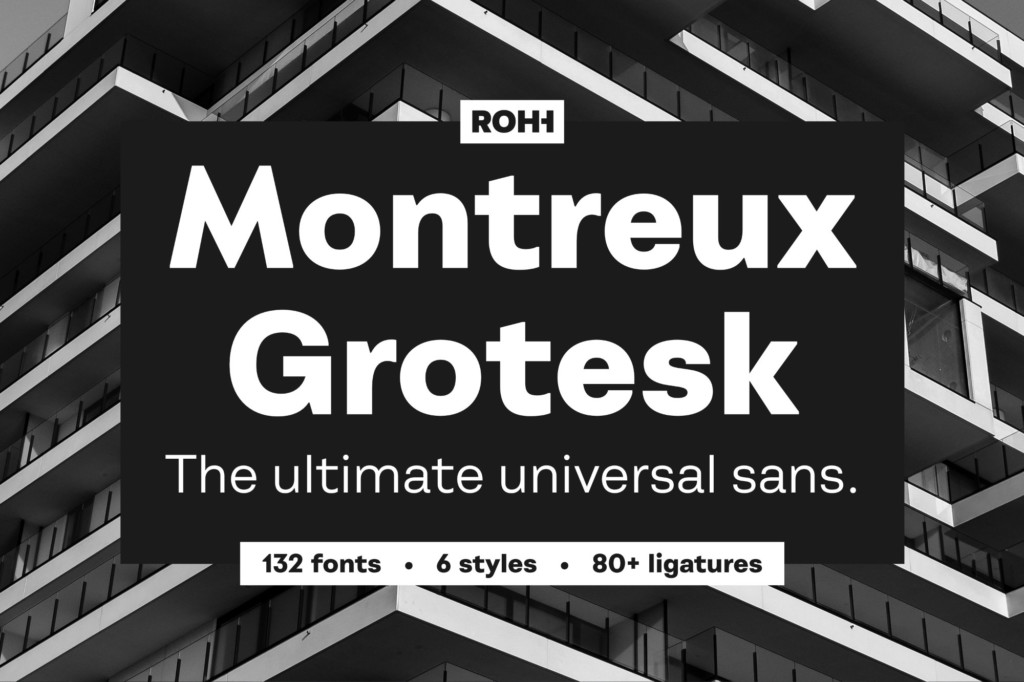
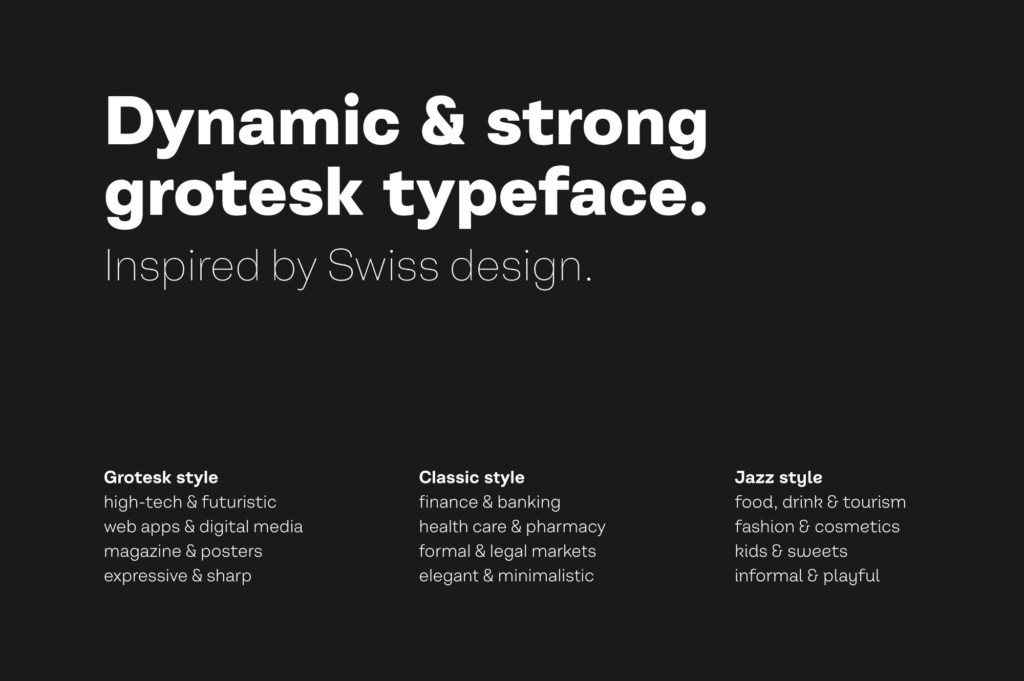
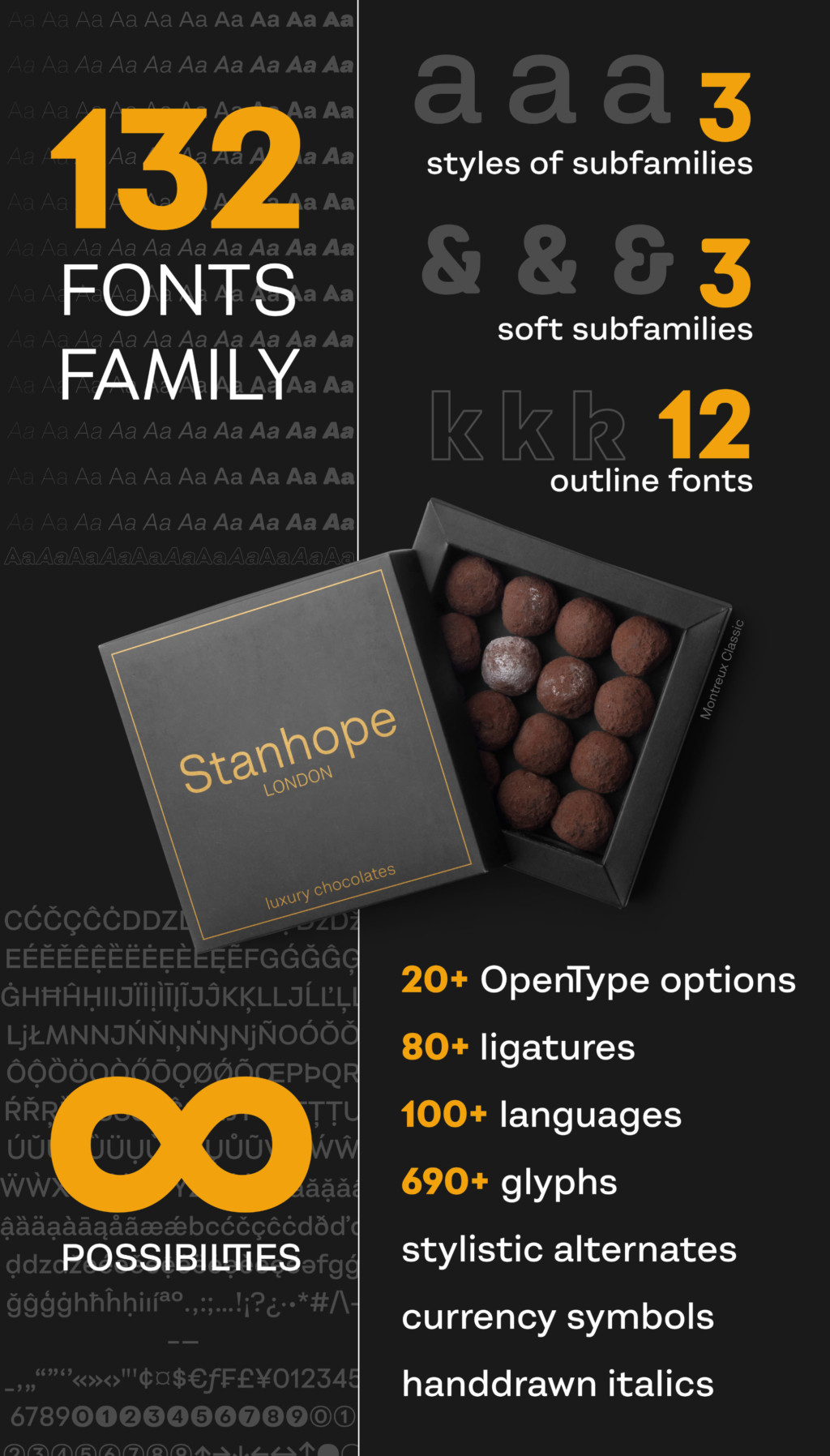
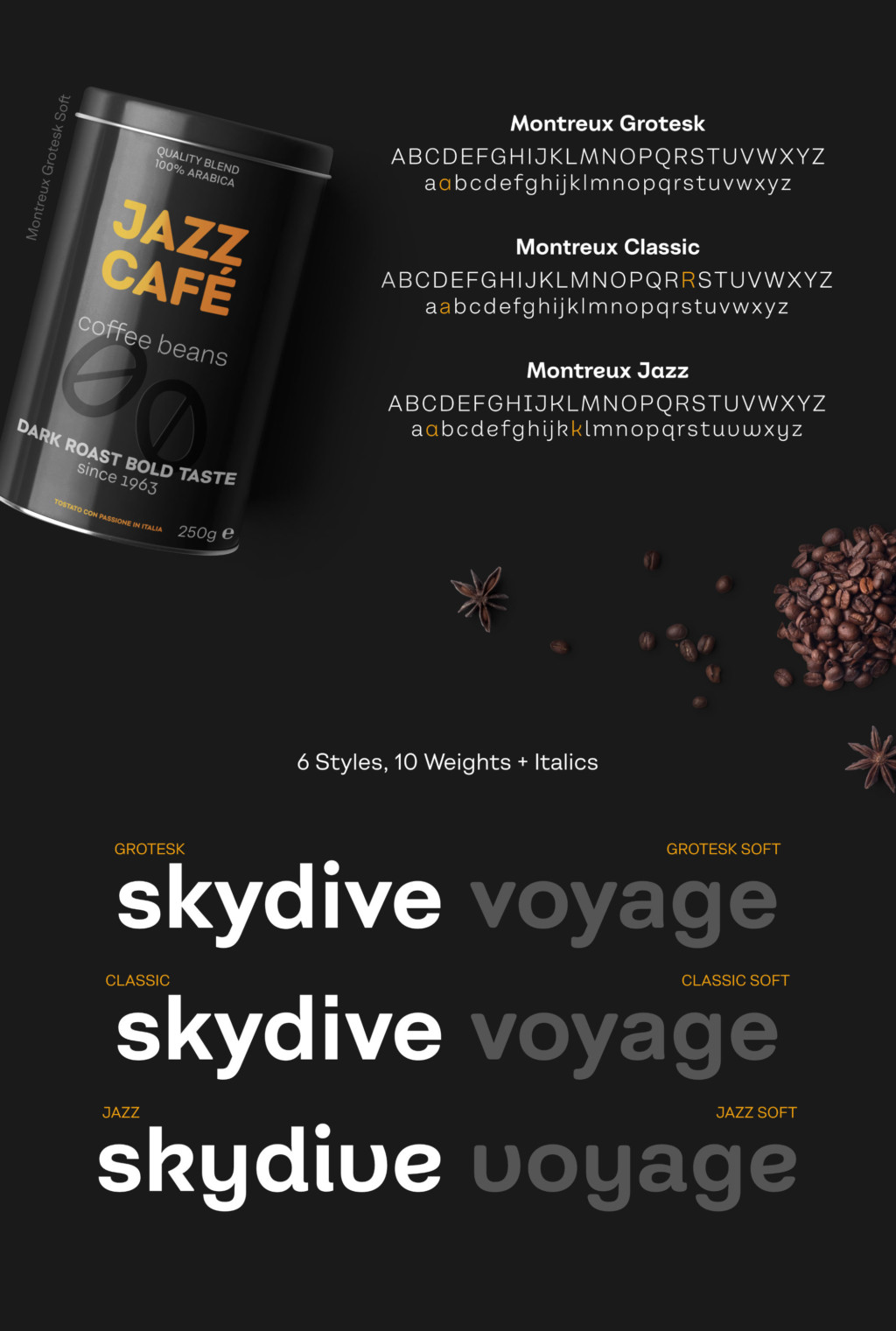
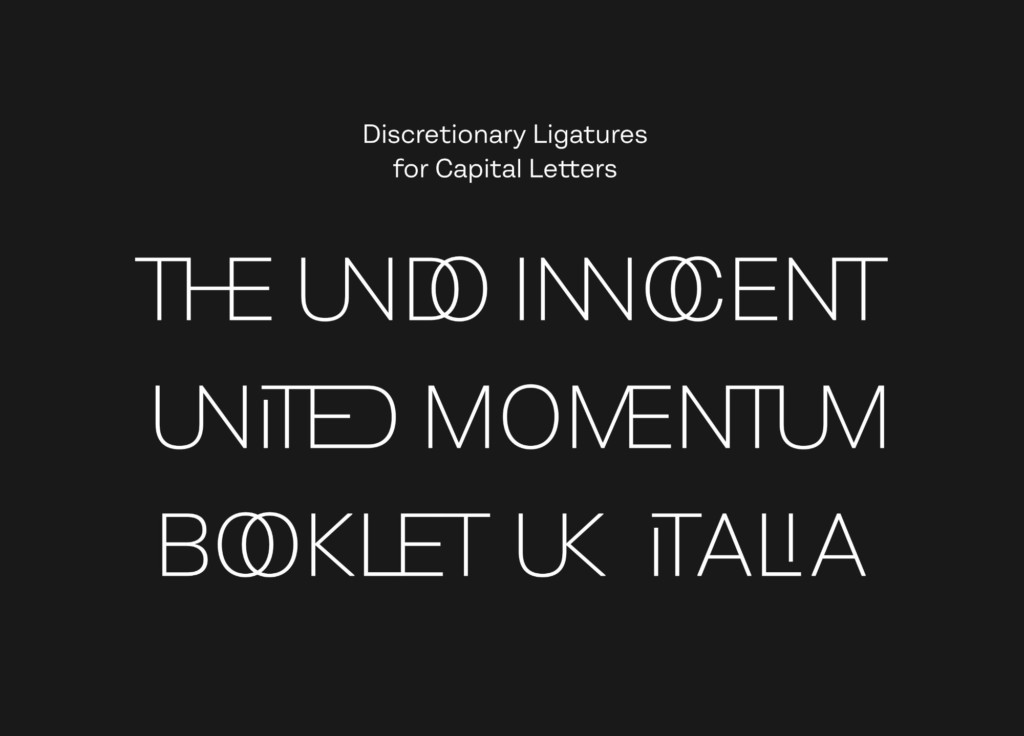
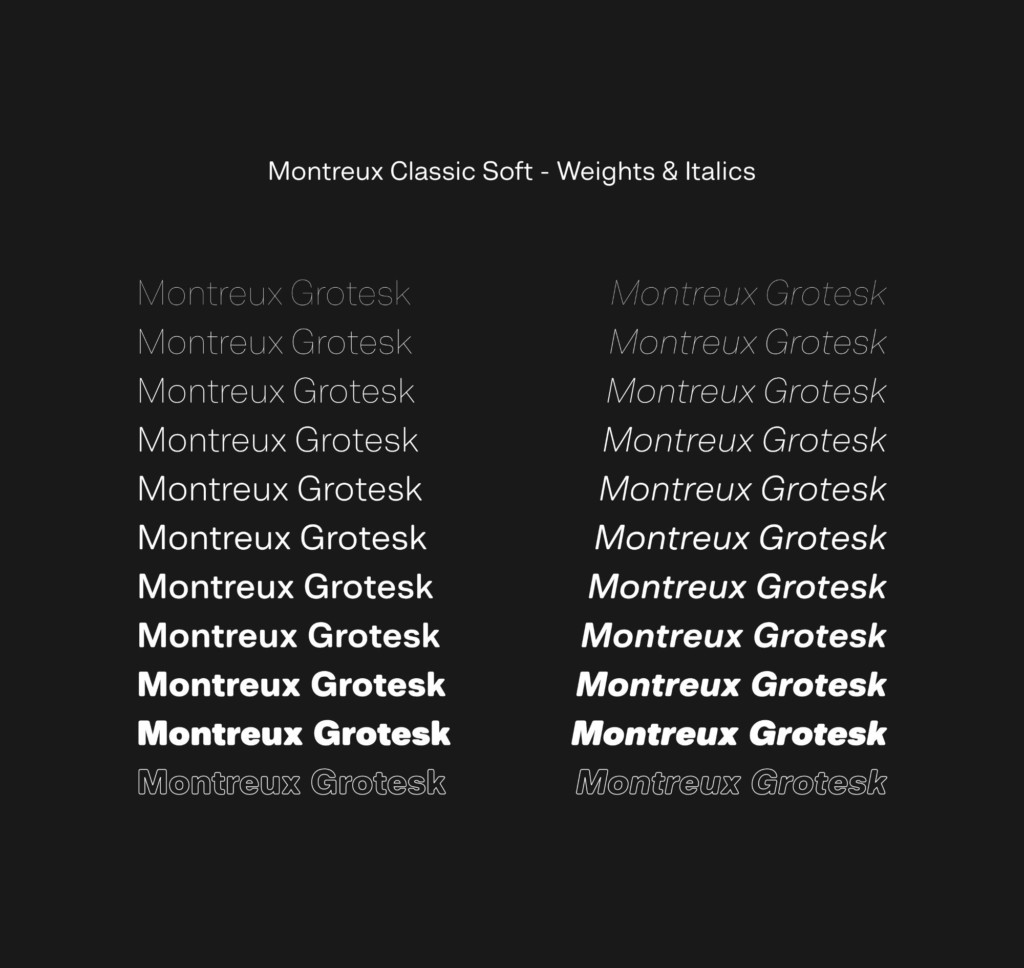
ヴィンテージ風フォント+オーナメントセット:PRESSBOX LETTERPRESS FONT COMBO
あえてウェイト違いの文字を混ぜた、ヴィンテージ風のかすれ加工済みフォント「PRESSBOX LETTERPRESS FONT COMBO」。飾りとパターンつきで、すぐにデザインが始められます。
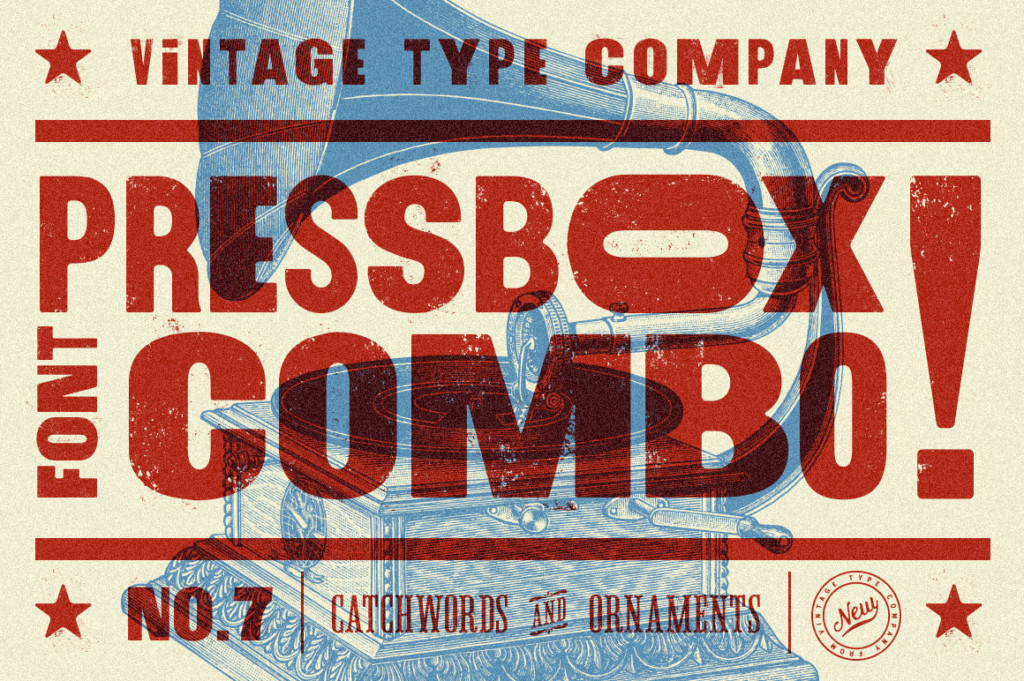
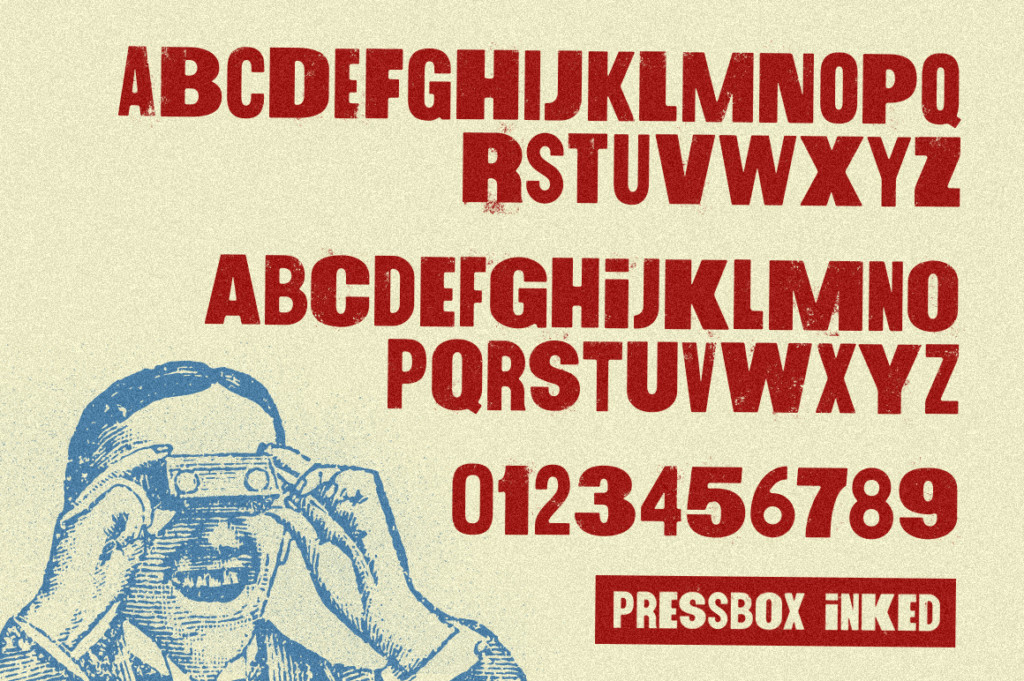
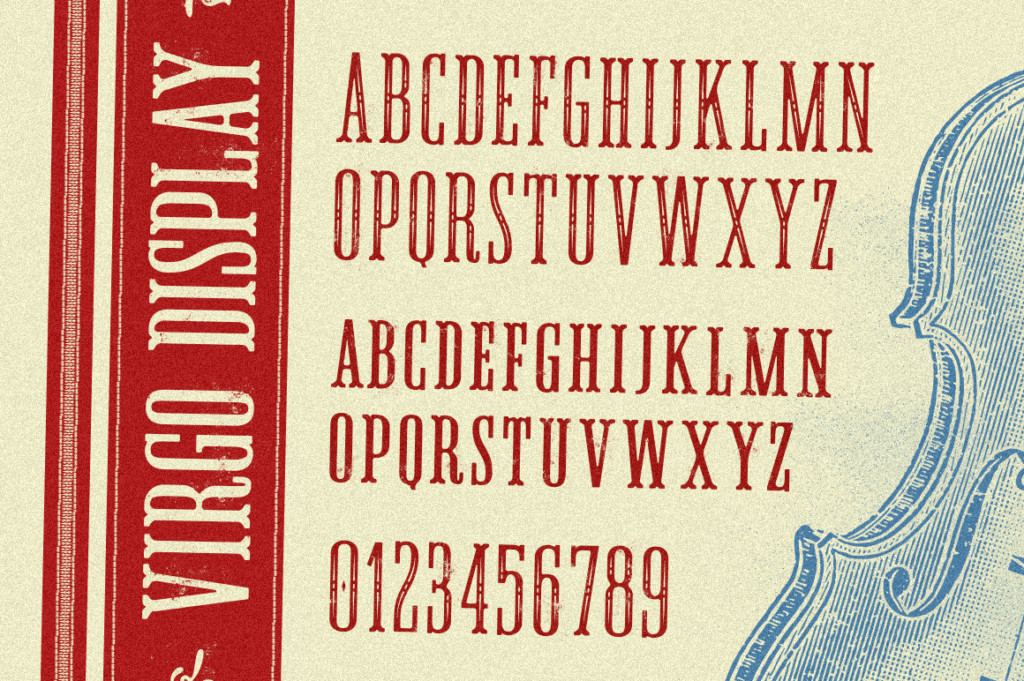
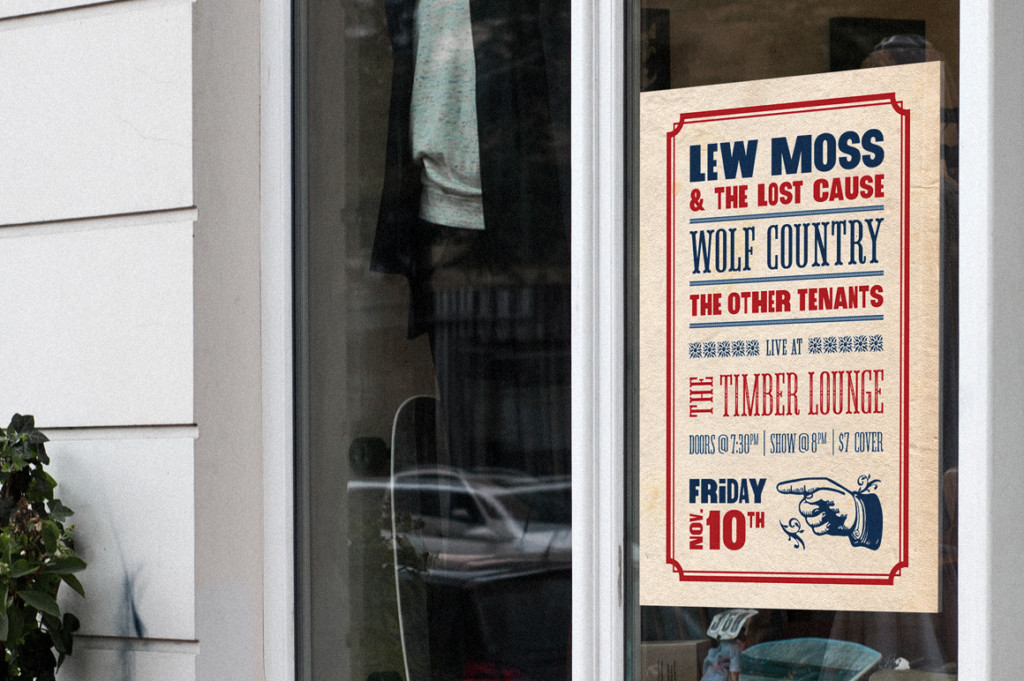
テクスチャつきのお得なフォントコレクション:MARYGOLD FONT DUO COLLECTION
セリフ&スクリプトフォントに加え、テクスチャも30種類収録した「MARYGOLD FONT DUO COLLECTION」。フォントは通常盤とSVG版が用意されていて、かゆいところに手が届くセットになっています。
難しそうな3Dスタイルもフォントを組みあわせるだけ!SANDWICH FONT
「SANDWICH FONT」なら、かなり複雑な作業が必要そうな立体文字も、数種類のフォントを重ねるだけで簡単に作れてしまいます。へこんだ文字も簡単に表現できますよ。